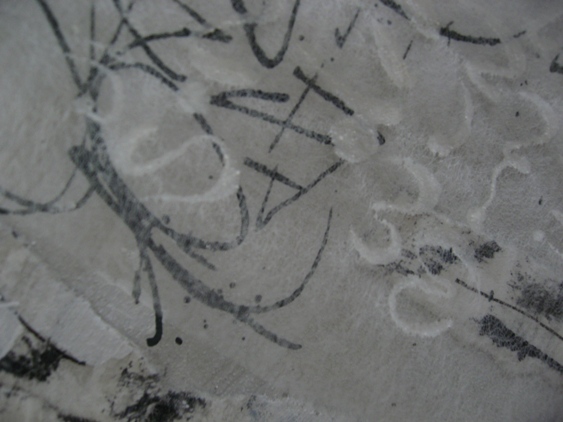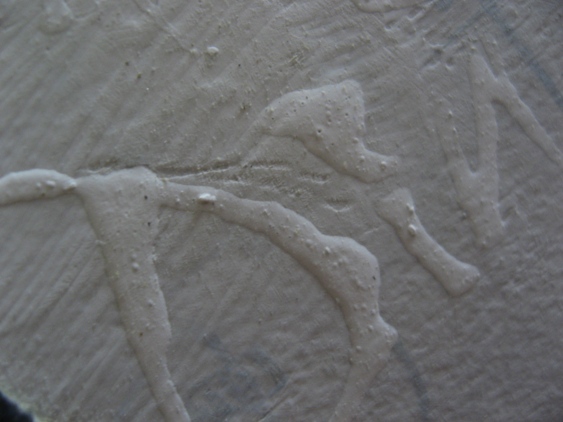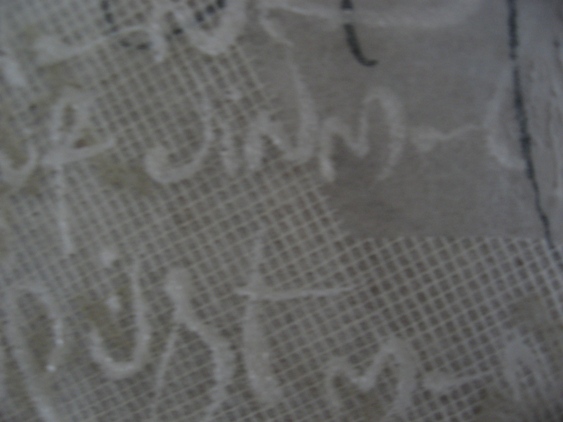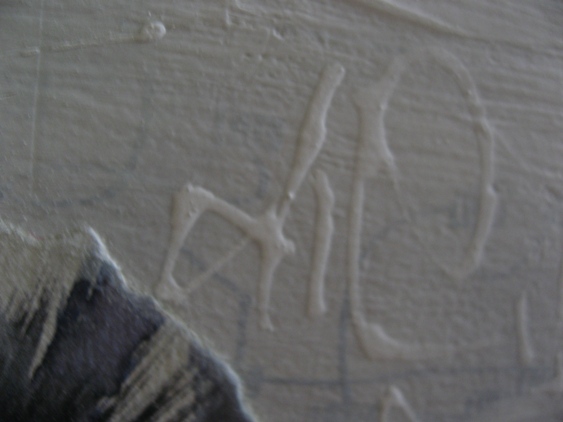
文字は浮くのか…それともへばり付くのか…?
最近はカリをしていますと、使う画材が変化している
こともあり…文字がどんな風に素材にのっていくのかが
気になります。
たいていは、着色した水彩紙や木炭紙などに
文字を書いていきますね…。
文字はお行儀よく、紙の上に並んでいき…、
ちゃんと付いている…という感じです。
でも、もの凄く薄い和紙や、寒冷紗などに文字を
のせると…なぜか、文字も浮いているような
錯覚を覚えます。
何だか遠慮しがちに…「わたし…浮き浮きです。」と
言っているかのようです…。
今度は、ものすごくベタベタに塗ったものの
上に文字がのりますと…。
これがなぜか、盛り上がってきます。
もちろん、ふつーのペンでは書きにくいので
ツールも変えますが…。
盛り上がる…というか…へばり付いているというのが
正しい表現かもしれません。
声を大にして「ファイト〜一発〜!へばり付くで〜!」と
言っているみたいです…。
・・・?・・・えっ?・・・
そうですね・・・きっと気のせいですね・・・。